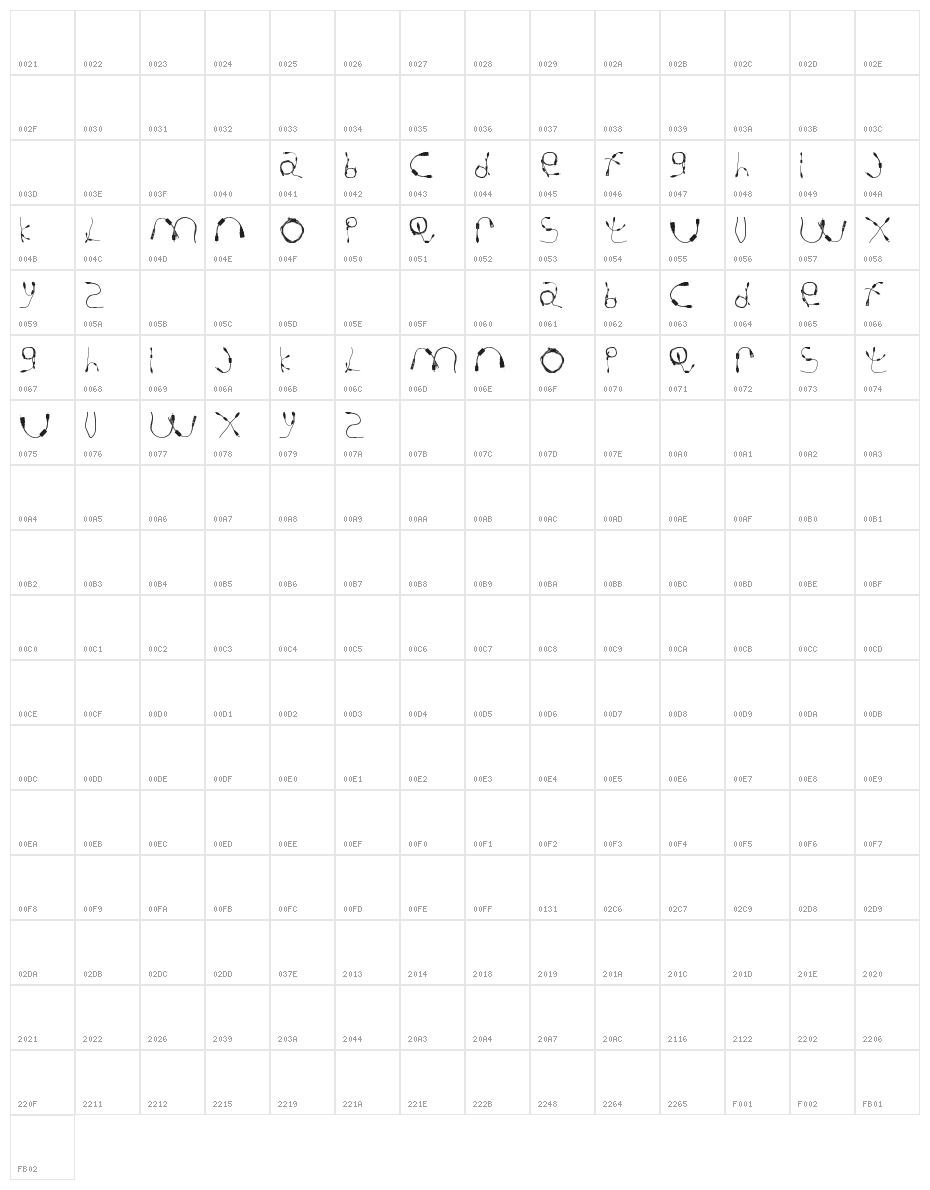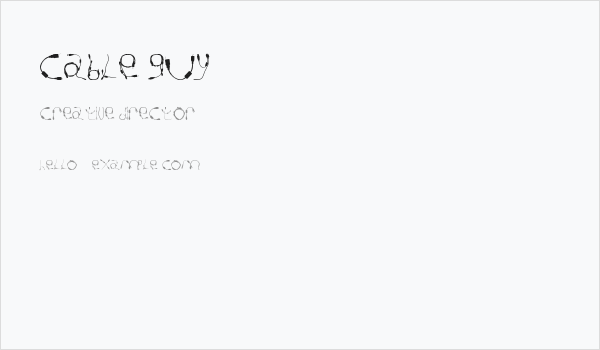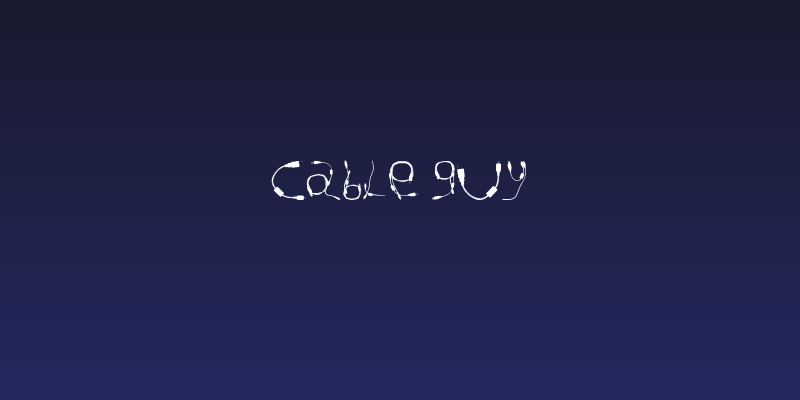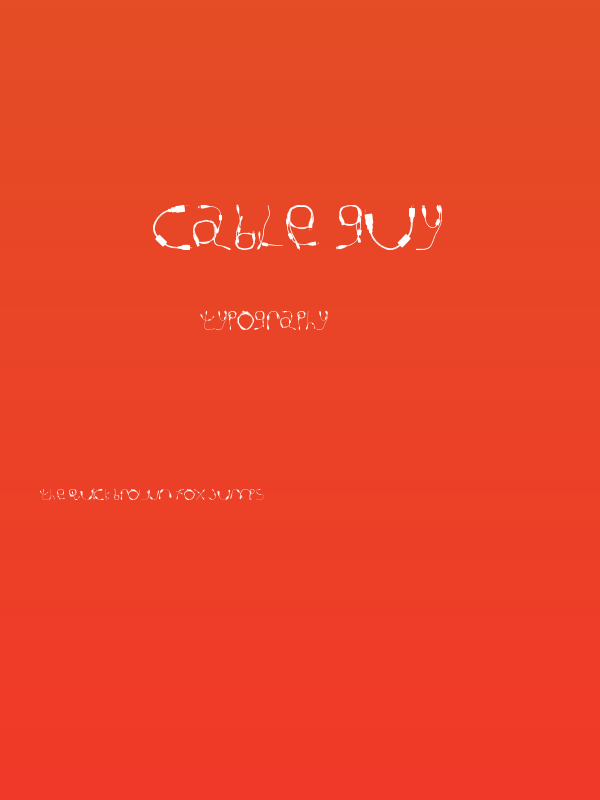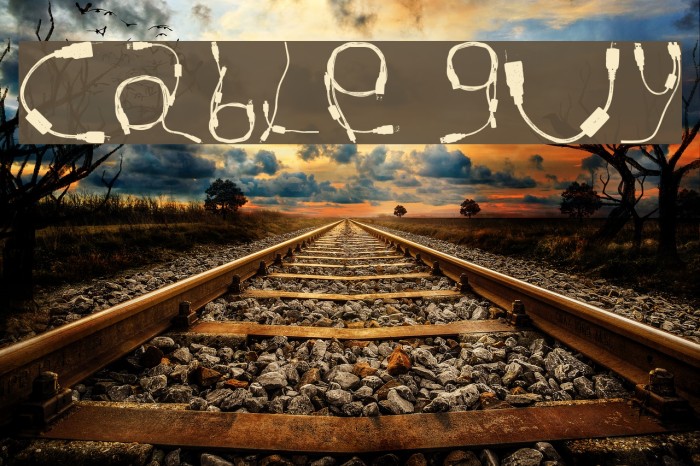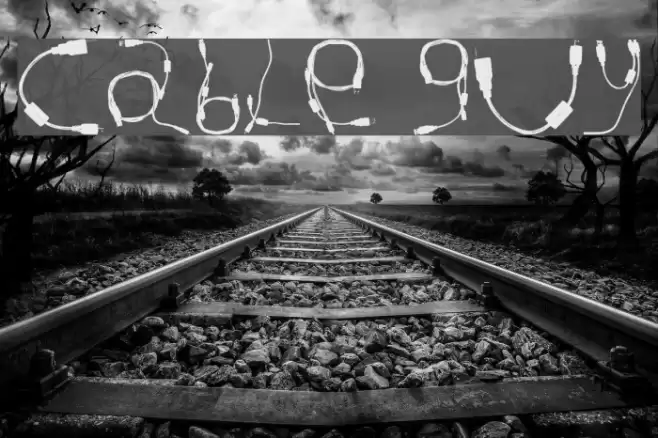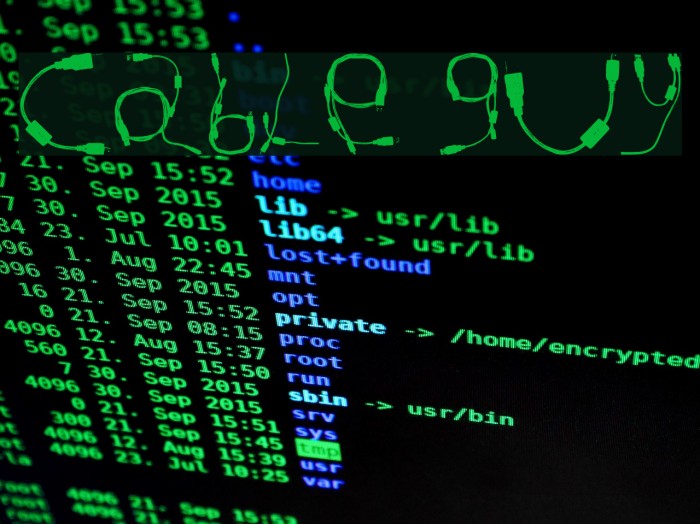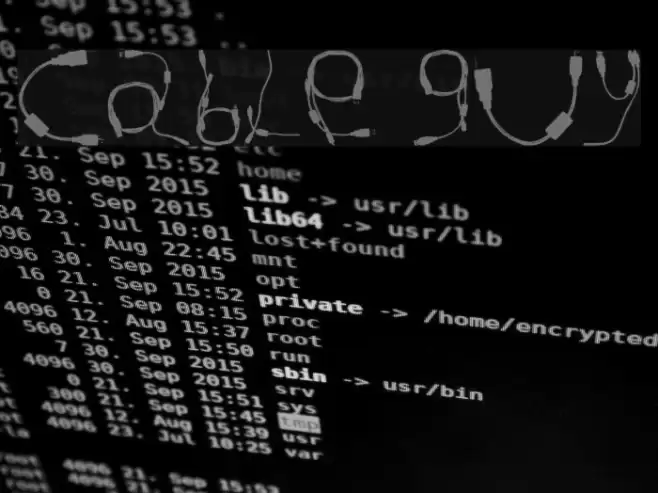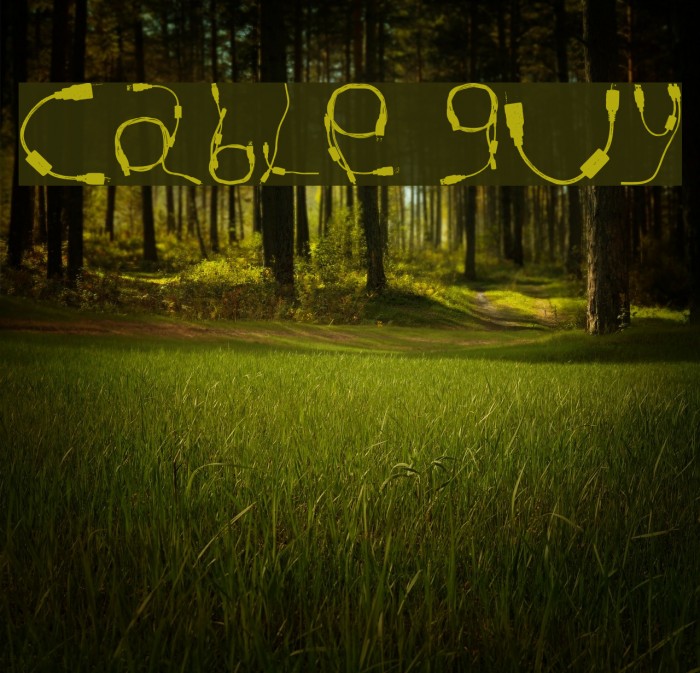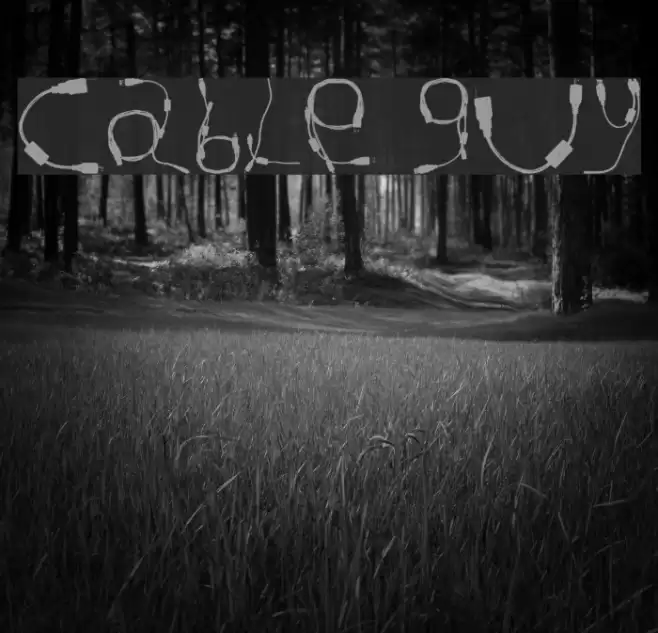
Cable Guy Font
| Caso de uso | Logos, Posters, Creative Displays |
| Projetos propostos | Ideal for tech-themed projects, creative posters, or branding for electronics and gadget companies. |